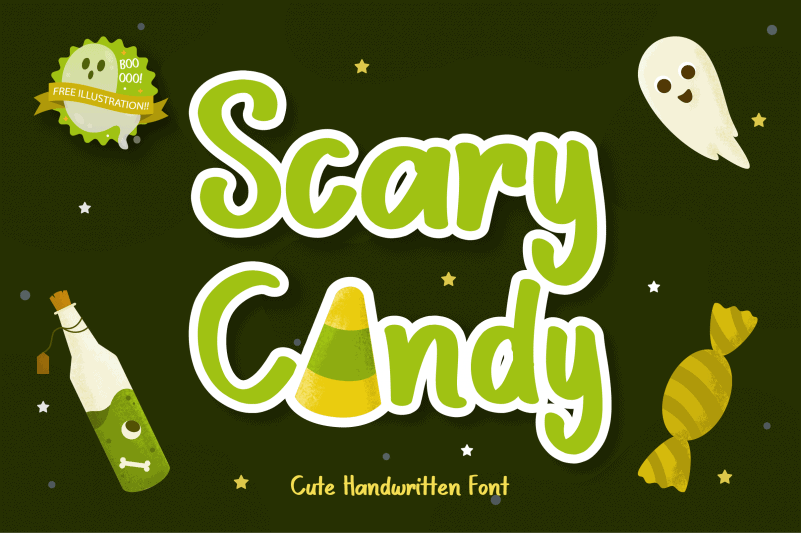
Scary Candy Script Font – Download Grátis
A Scary Candy Script Font é uma fonte que combina a leveza e a misteriosa elegância de Halloween numa única peça. Perfeita para qualquer projeto que reúna ilustrações com letras, sua naturela e singularidade a tornam um acréscimo inegável em designs infantis, desde cartões de boas-vindas até trabalhos de moda ou camisas personalizadas. Este design perfeito para festividades como Halloween também é ideal para aqueles momentos de diversão e criatividade, permitindo que você explore a sua imaginação à vontade. Seja para criar cartões de aniversário para o seu filho, artigos de moda ou até mesmo roupas personalizadas, a Scary Candy Script Font certamente faz do seu design um momento inesquecível.